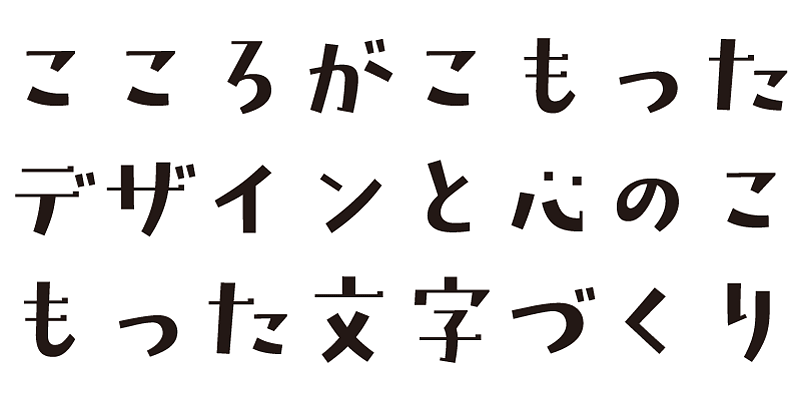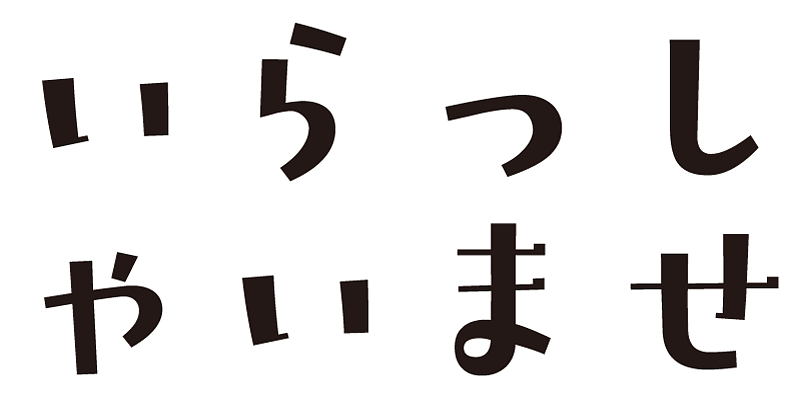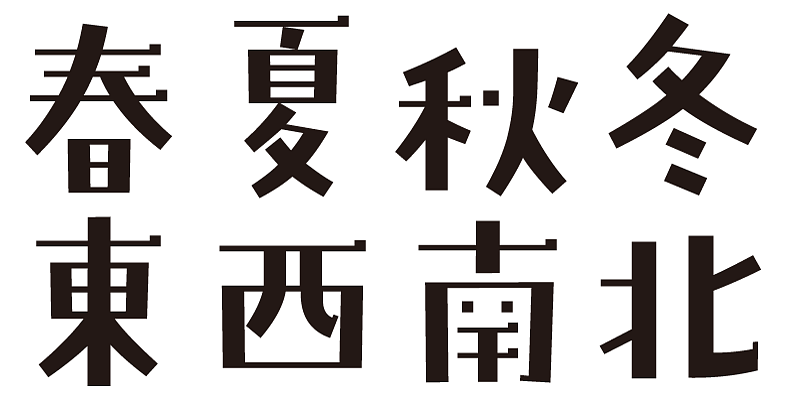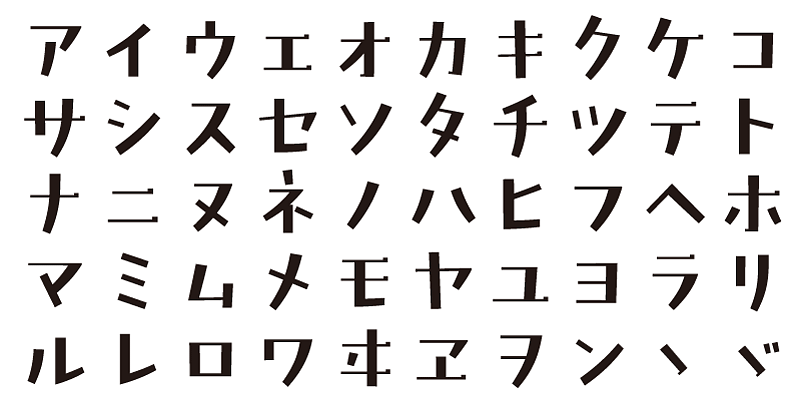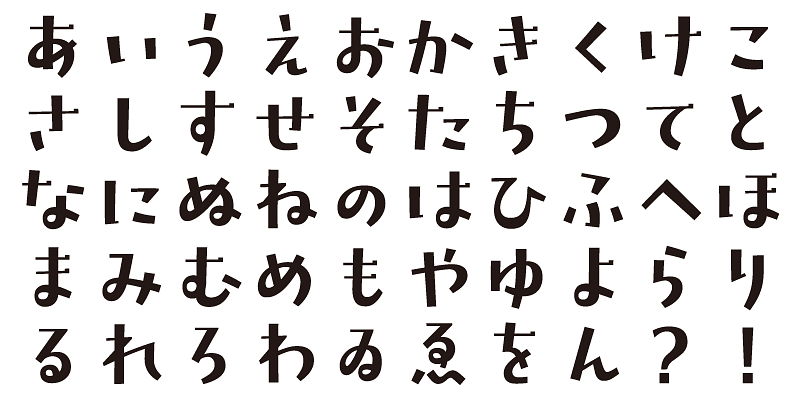
Este tipo de letra evoca nostalgia, calidez, sabor y tranquilidad, recordando la buena y antigua era Showa.
Incluye 1000 caracteres kanji, además de hiragana, katakana, caracteres alfanuméricos y signos de puntuación.
Diseñamos tipos de letra con la esperanza de que añadan un significado subyacente a las palabras escritas. Queremos que el usuario se sienta bien, con comodidad y alegría al utilizar estos tipos de letra.